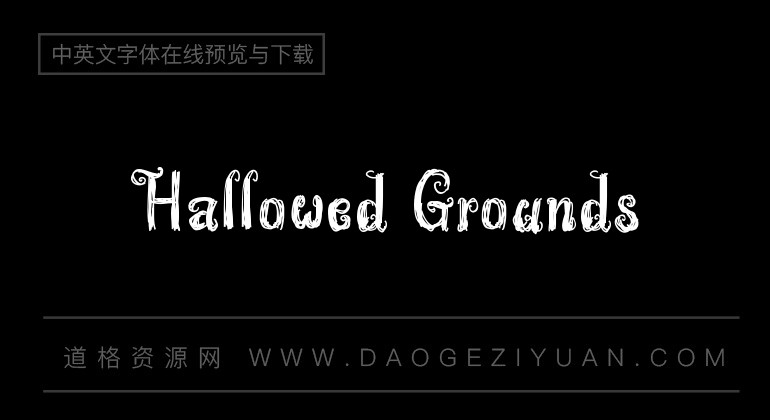
Hallowed Grounds 是一种免费的手写字体,由美国设计师 Jeremy Vessey 创建。这个字体的特点是它看起来非常自然,就像是手写的一样,同时也非常易于阅读。Hallowed Grounds 字体适用于许多不同的项目,包括印刷品、网站设计、海报、书籍封面和标志设计等。该字体包含大写和小写字母、数字、标点符号以及一些特殊字符,可以在多种设备和软件上使用。内容介绍
Hallowed Grounds是一款非常不错的手写艺术字体,具有很好的视觉感,适合于文化类的宣传设计、商业类品牌的广告和产品包装设计以及个性化文字排版等较多场景。